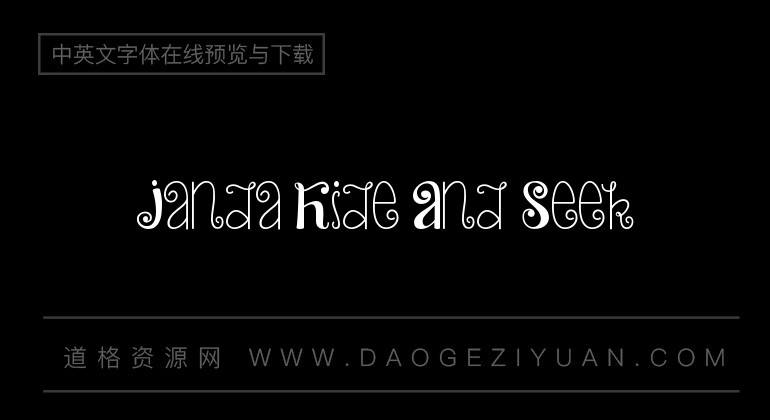
Janda Hide And Seek
Janda Hide and Seek是一种手写字体,由Kimberly Geswein设计。它的特点是字母的线条充满了动感和生气,字母之间的间距也比较不规则,给人一种随性和自由的感觉。这种字体适用于设计卡片、海报、标志、书籍封面等需要手写风格的场合。它的造型类似于儿童的书写,因此也常被用于设计与儿童相关的主题。Janda Hide and Seek字体有多种字重,可以根据需要在设计中使用。
Janda Hide And Seek是一款非常不错的手写艺术字体,具有很好的视觉感,适合于文化类的宣传设计、商业类品牌的广告和产品包装设计以及个性化文字排版等较多场景。